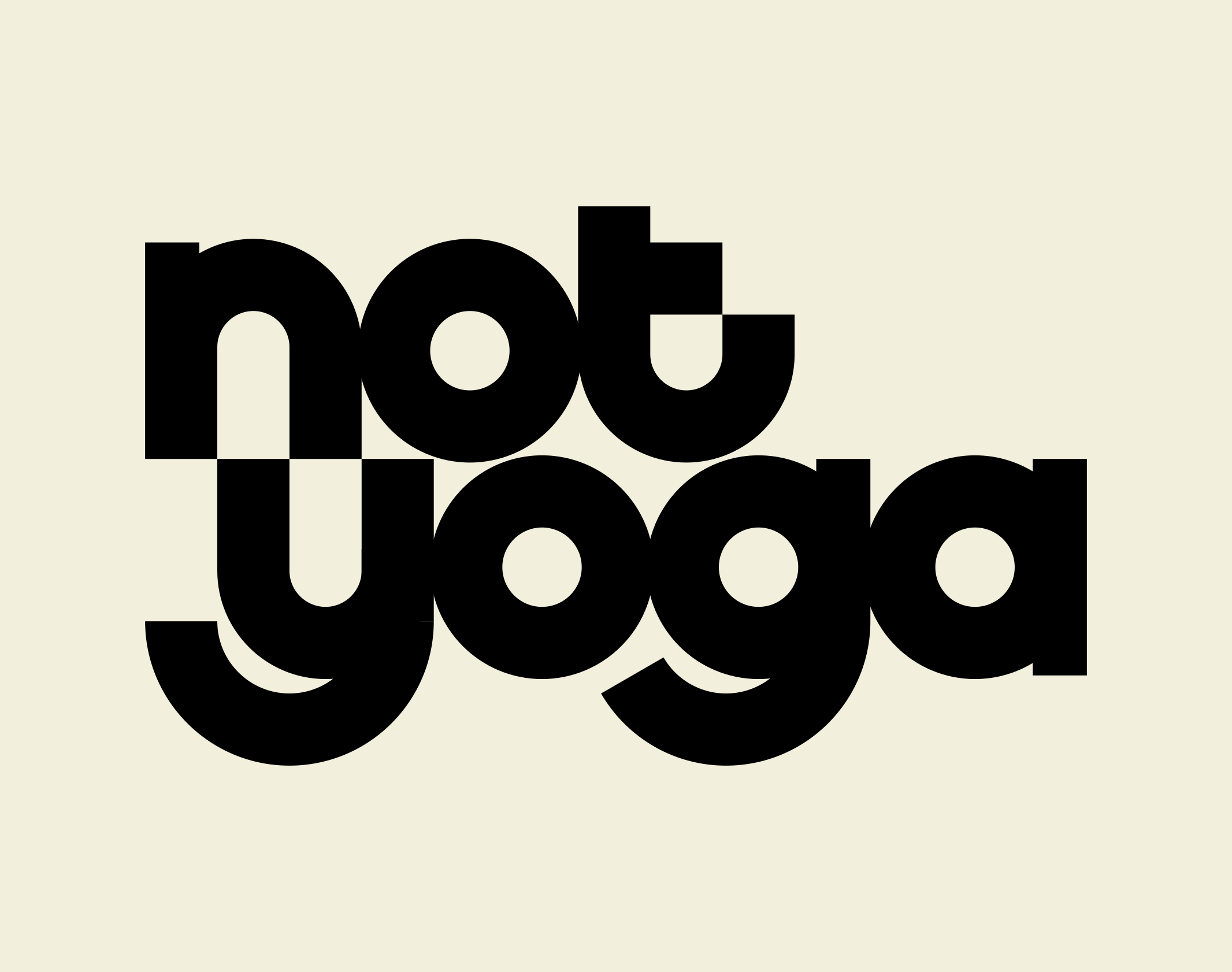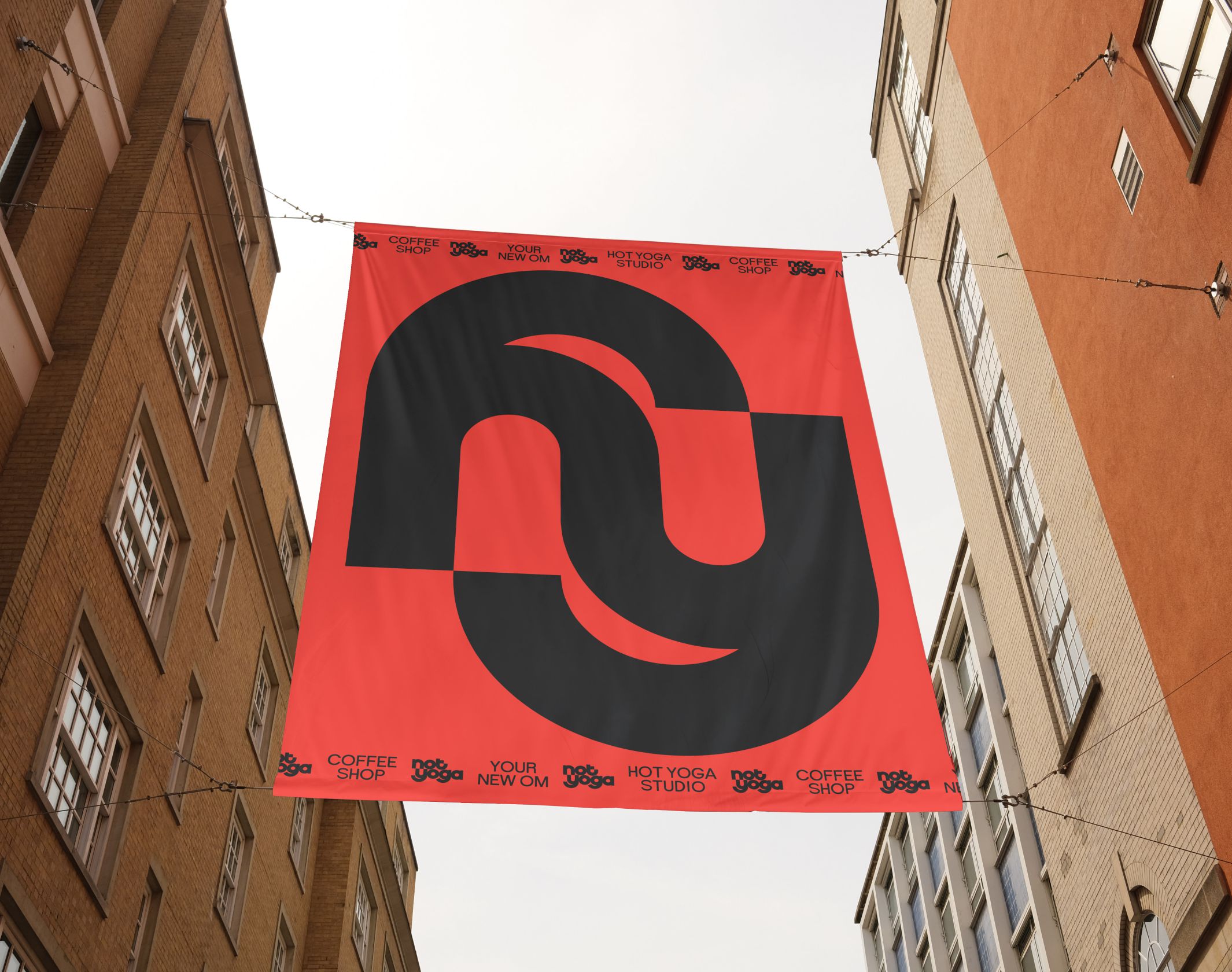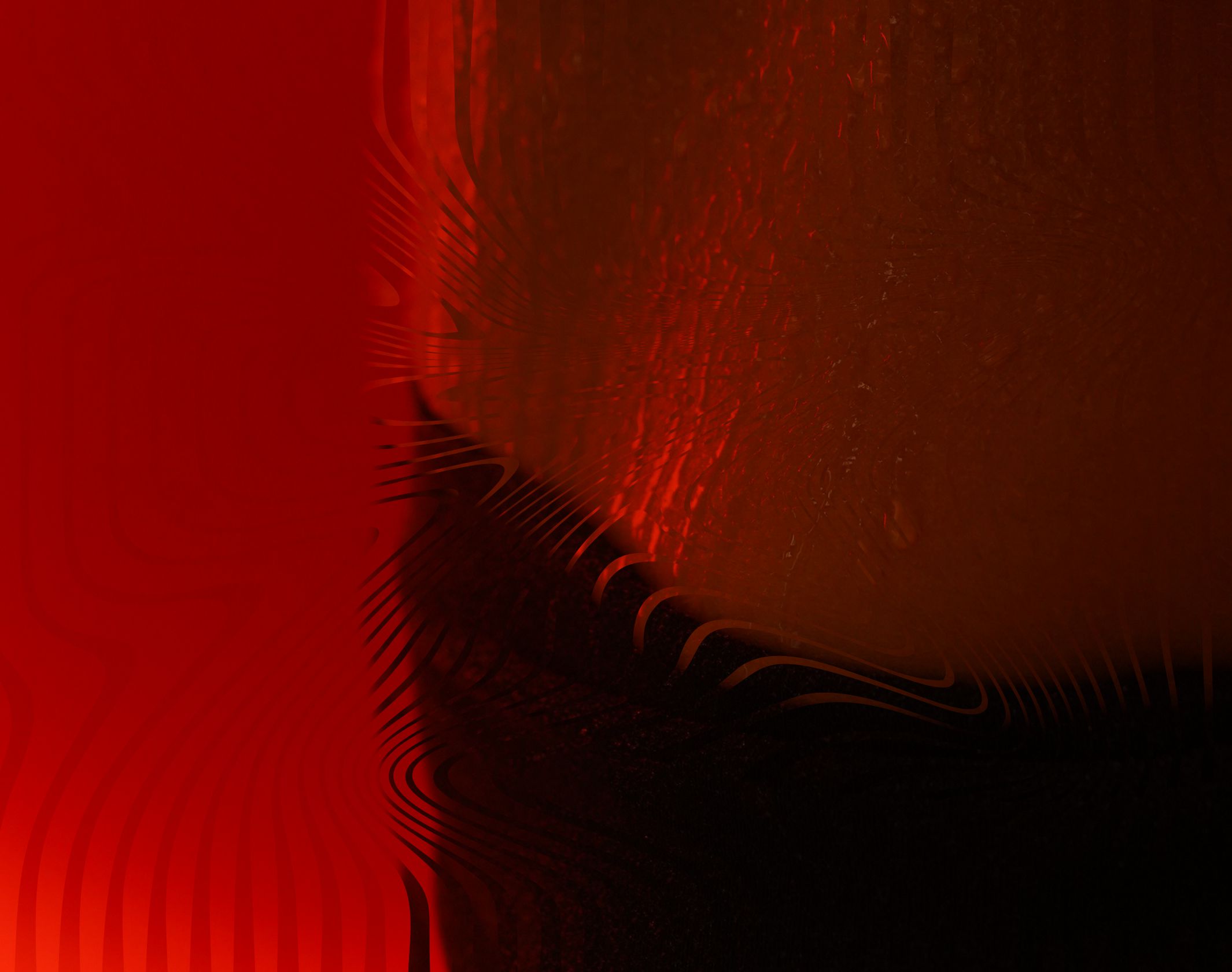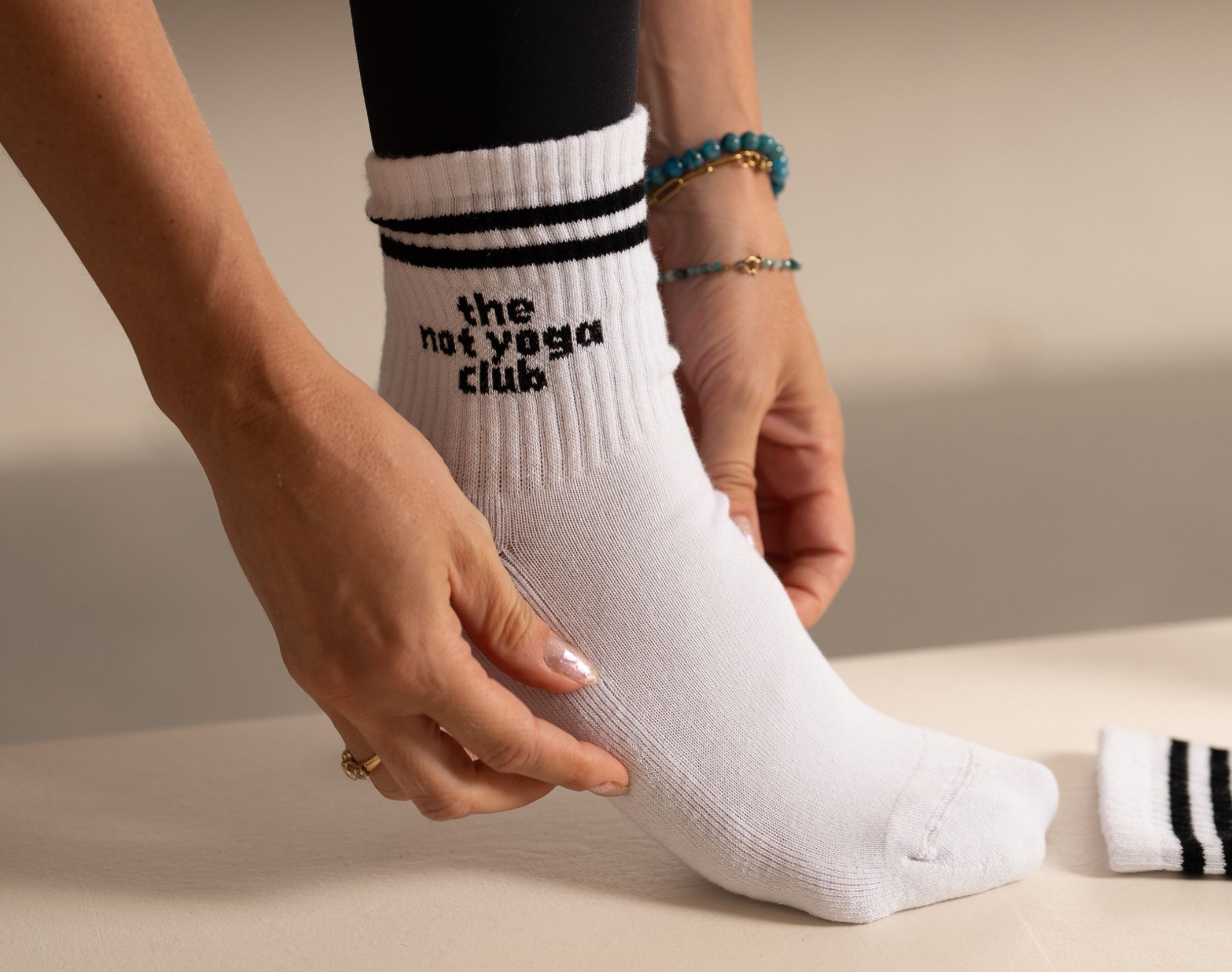
Not Yoga
Your New Om. Au 13 rue des tournelles à Paris, le studio Not Yoga offre un cours dynamique d’une heure, pour tous niveaux, en se concentrant sur les postures. Son concept se veut purement corporel et dénué de spiritualité (pas de mantras ni de chakras). La pratique se déroule dans une salle chauffée à 33°C par infrarouge, visant un effet détoxifiant, dans une atmosphère intimiste et sans distraction (lumière tamisée, sans miroirs).
Brand Brothers a été missionné pour définir l’identité visuelle intégrale du lieu. Le logotype, géométrique, stable et confiant, est basé sur des équilibres qui offrent aux deux termes composant le nom, une imbrication particulière. Cette structure se décline en un monogramme symétrique, emprunt de puissance et de rondeur, un emblème moderne en perpétuel mouvement. Le système graphique raconte le yoga autrement, en évitant les recours classiques : un pattern déformé, libre, ondulant au gré du flow. Cette approche brute et contemporaine offre à Not Yoga une grammaire visuelle modulaire et hypnotique, déclinée sur du print, des objets et sur l’environnement digital.